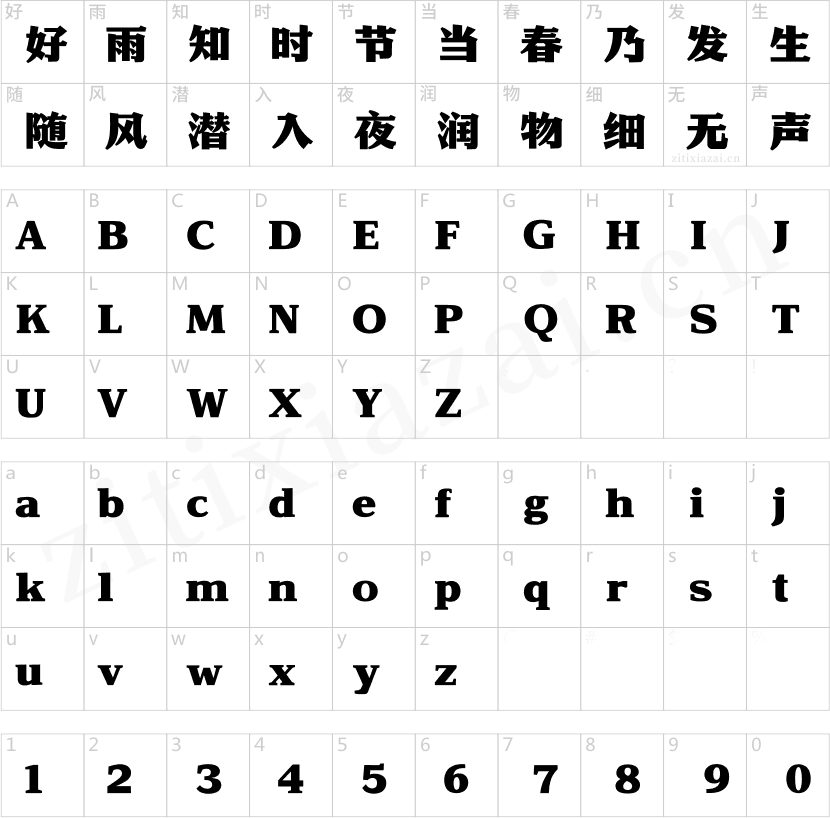
Aa黑宋
Aa黑宋字体
Aa黑宋是一款非常具有艺术性的字体,它的设计灵感来源于对古典艺术的研究,同时又融入了现代字体设计的元素。字形优美,笔画粗细变化自然,给人以大气、典雅的感觉。Aa黑宋是一款既传统又现代的字体,它的设计充满艺术感,美观大方,实用性也非常强。无论是对于设计师还是对于普通读者来说,都是一种非常不错的字体选择。Aa黑宋适合用于具有艺术感的场合,比如海报、宣传单张、书籍封面等。由于其字形流畅且具有动态感,也适合用于大量的文本排版,如报纸、杂志等。
- 字体名称:Aa黑宋
- 字体全名:Aa黑宋